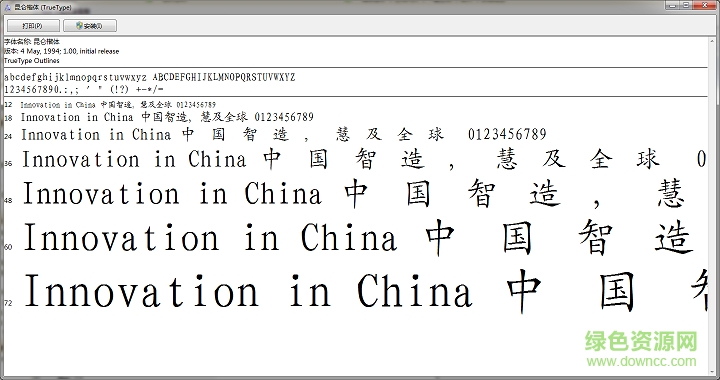
昆仑楷体字体
昆仑楷体是一款非常美观的楷书字体,这款字体笔画细腻,字体方正,不少朋友都比较喜欢,适合用于多个不同领域使用,有需要的用户赶快下载体验吧!
昆仑楷体
楷书介绍
楷书也叫正楷、真书、正书。从程邈创立的隶书逐渐演变而来,更趋简化,横平竖直。《辞海》解释说它“形体方正,笔画平直,可作楷模。”故名楷书。始于汉末,通行至现代,长盛不衰。
楷书的产生,紧扣汉隶的规矩法度,而追求形体美的进一步发展,汉末、三国时期,汉字的书写逐渐变波、磔而为撇、捺、且有了“侧”(点)、“掠”(长撇)、“啄”(短撇)、“提”(直 钩)等笔画,使结构上更趋严整。如《武威医简》、《居延汉简》等。楷书的特点在于规矩整齐,是字体中的楷模,所以称为楷书,一直沿用至现代。